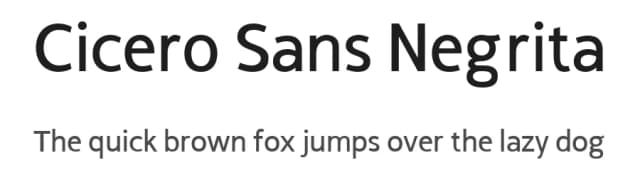
About Cicero Serif Font
esta fuente ha sido co-diseñada junto a Lizette hechevarria
tiene diseñada sus variantes san serif, italica, versalita, book y ligth.
| Designer | Lizette Hechavarría Pilia y Ernesto Antón Peña |